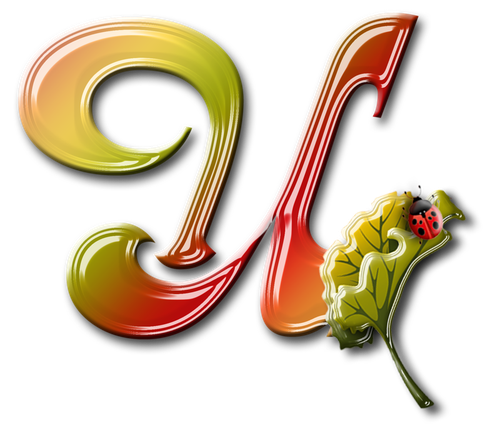
Мы продолжаем серию коллекцию с материалами для веб-дизайнера. И сегодня это эффекты текста в фотошопе . Использование красивого текста является важным фактором в процессе создания хорошей графики и привлекательного оформления.
Созданные эффекты представляют из себя исходные файлы формата psd, с редактируемыми слоями. В некоторых случаях это даже редактируемый текст, так что не делая особых изменений, вы можете применить представленные эффект к своему тексту. Ниже представлен список эффектов, которые находятся в вашем распоряжении.
1 → Золотой + Стеклянный эффект
Это несколько текстовых слоёв для веб и графического дизайна, для создания интересных эффектов для текста в стиле “золото” и “стекло”. К архиву прилагается стиль фотошопа.asl, который можно сохранить в наборе, и использовать в любое время.
2 → Размытый текст
Ещё один эффект размытых слов в объёме.
3 → Металлический текст + шрифт к нему
Довольно реалистичные металлические буквы с подходящим шрифтом. Данный шрифт находится в архиве вместе с исходником.
4 → Ещё исходник стиля букв в приятных тонах
Тоже неплохой стиль, с небольшим 3D
5 → В стиле Glamour
Простой, но привлекательный текст в красном стиле, без применения дополнительных слоёв, только параметры наложения.
6 → Вдавленные буквы с 3D эффектом: PSD + шрифт
Эффект вдавленность букв достигается нехитрыми манипуляциями, в частности, внутренней тенью, которая как раз и создаёт такую видимость. К макет приложен также шрифт, использованный в данном тексте.
7 → Вдавленный текст
Самый простой пример применения такого эффекта. Всё манипуляции в параметрах наложения. Исходник ниже.
8 → В стиле Retro school
Интересный эффект ретро достигается путём компоновки параметров наложения, а также текстуры, которая создаёт видимость старых букв.
9 → Превосходный 3D текст “Grand”
Очень профессиональная работа. Реалистичные эффекты в автоматическом режиме, исходник mock-up типа. К архиву прилагается 2 используемых шрифта, и сами эффекты в двух вариантах.
10 → Рукописный текст
Хорошее сочетание рукописного шрифта и стиля текста. Сам файл шрифта прилагается.
11 → Эффект “Authentic”
На любителя. Mock-up PSD исходник.
12 → Элегантный белый в стиле “Soft”
Привлекательный эффект, простой, но в то же время интересный результат получается.
13 → Расписной зеркальный текст
Элегантный шрифт (прилагается), красивый зеркальный текст.
14 → Золотые буквы с зеркальным отражением
Очень реалистичный эффект, максимально соответствующий золотой поверхности. При всё такого эффекта можно добиться одними средствами параметров наложения, так что вы сможете без труда ещё добавить ещё один стиль в свою коллекцию.
15 → Отражающийся глянец
Простой, но также приятный эффект текста в фотошопе, представляющий глянец, с зеркальным видом и интересным шрифтом.
16 → Морозный эффект в ледниковом стиле
Довольно интересный ледяной текст, очень подходящий шрифт + параметры в фотошопе позволили добиться такого морозного стиля.
17 → Буквы в стиле мыльных пузырей
Для того, чтобы создать быстро и красиво надпись в фотошопе, возьмите за основу специальный мануал, которым можно будет воспользоваться в любой нужный момент.
— откройте фото;
— найдите требуемый инструмент, он выглядит как буква «Т»;
— кликните на то место, на котором должен оказаться текст. Впишите текст;
— чтобы изменить тип и размер шрифта, расположение и цвет надписи – следует воспользоваться специальными клавишами, которые открываются в специальном окне;
— настраиваем настройку деформацию текстов, при помощи специальной кнопки;
— чтобы убрать рамку, которая автоматически появилась вокруг текста, нужно сменить стиль слоя.
Для этого перейдите в специальное окно и выберете там слой со своей надписью;— в новом окне стилей настройте тени, как Вам кажется лучше, а также используйте обводку и другие доступные эффекты;
— мышью просто перетяните блок с надписью в часть фотографии. Сохранив изменения;
Вот так мы и получим стандартный вид текста на картинке с помощью фотошопа.Здесь описана возможность создания надписи, выполняя специальную установку шрифтов из других – дополнительных источников, создаем заливку градиента и обводку.
Выберете пункт «Горизонтальный текст ». Напишите этот текст в любом месте на фото. С помощью специальной панели выберите требуемый шрифт.
Далее нужно подобрать размер текста (символов). После чего уже перейти к добавлению специальных эффектов. Откройте вкладку «Окно », далее «Слои ». Перейдите к слою с текстом. В специальном окне стиля добавьте тень. Добавьте 75% непрозрачности на параметре. Совмещение установите на 10 или 12 пикселей, ровно так же на значение 10-12 установите ползунок размера.
Стиль шрифта